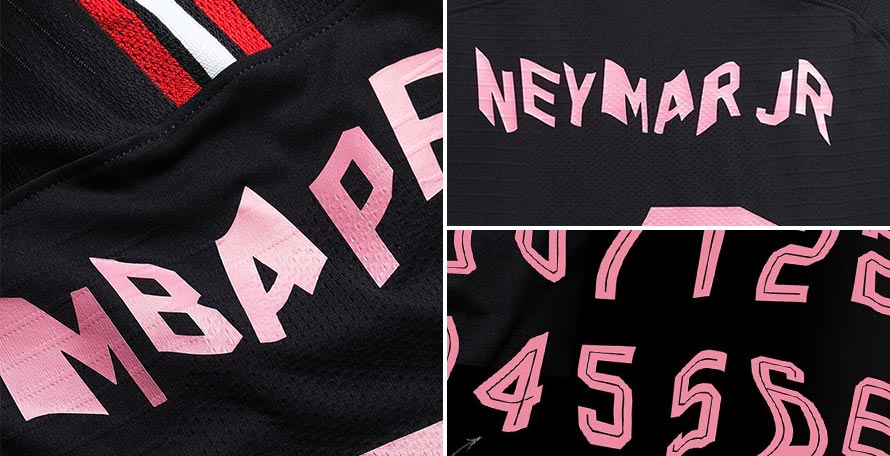
Special-Edition Nike x PSG x Tyrsamisu Schriftart enthüllt
Paris Saint-Germain hat heute eine einzigartige neue Schriftart als Ergebnis einer neuen Zusammenarbeit mit dem Pariser Künstler Tyrsamisu enthüllt. Diese exklusive neue Schriftart wird nur heute bei der Champs-Élysées Boutique erhältlich sein und nicht auf dem Platz verwendet werden.
Nur die Trikots der Jordan x PSG Kollektion sind für die Personalisierung mit der von Tyrsamisu entworfenen Schriftart erhältlich.
Der Pariser Künstler hat eine überraschende und originelle Schriftart entworfen, die Basketball und Fußball vereint. Die erhältlichen Nummern und Buchstaben haben faszinierende Formen, womit er mit den üblichen Designcodes im Fußballs brechen will.
Eine weitere Idee hinter dieser neuen Schriftart ist auch, ein personalisierteres Trikot zu bieten. Aus diesem Grund hat jeder Buchstabe und jede Nummer zwei Versionen. Damit werden Käufer in der Lage sein, die Kombinationen zu vervielfachen und dank der Schriftart ein einzigartigeres Trikot zu erhalten. Zu guter Letzt befindet sich innerhalb der schwarzen Zahlen eine schwarze Linie, ein Detail, das auch auf der normalen PSG Champions League Schriftart zu finden ist.